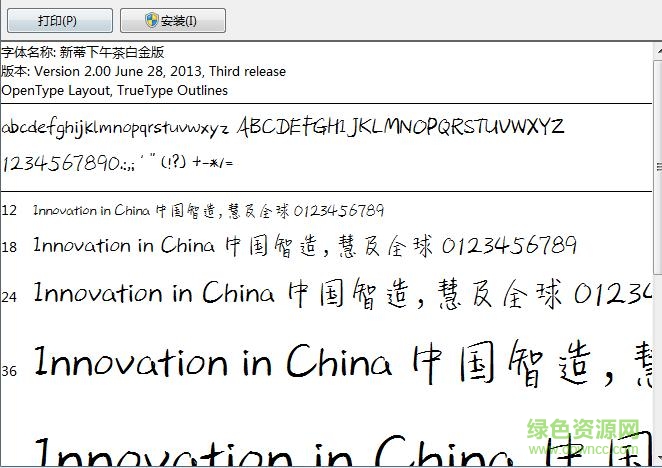
新蒂下午茶白金版是一款由新蒂字體打造的全新的中文字體,延續(xù)了經(jīng)典下午茶字體的所有特色,加入了更多的字節(jié),讓這款字體更加的完善,有需要可以下載使用!
新蒂下午茶白金版是經(jīng)典新蒂下午茶體的最新修訂版本,相較于專業(yè)版和基礎(chǔ)版,這個(gè)版本的字庫更加的全,更加適合用來進(jìn)行藝術(shù)創(chuàng)作!